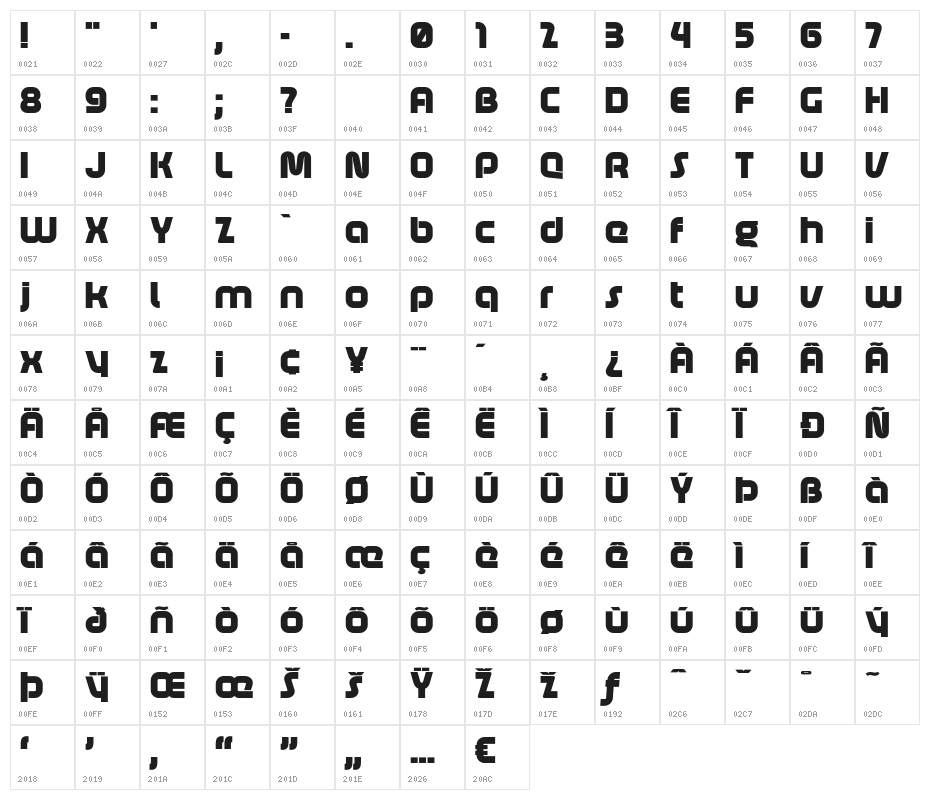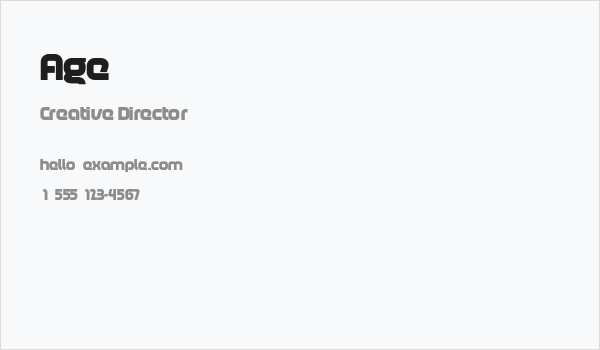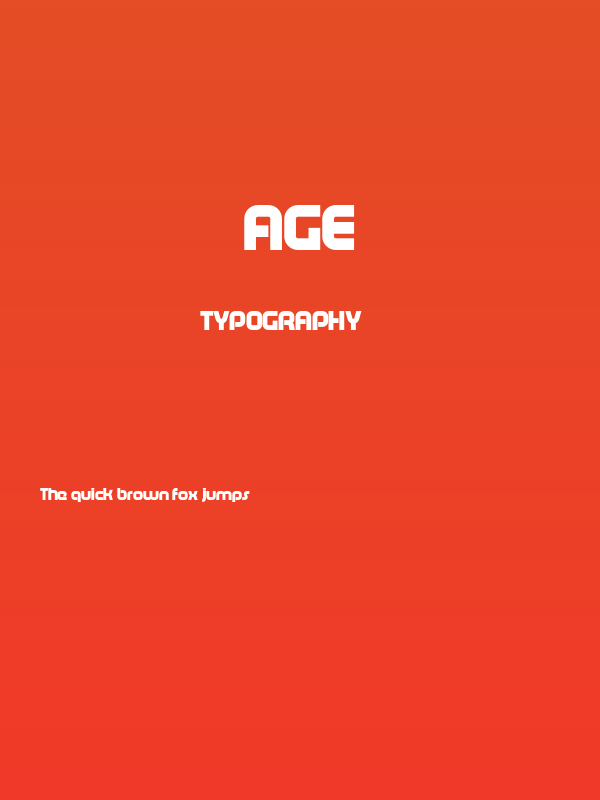
Age Font
✎ Round
| カテゴリ | Round |
| おすすめプロジェクト | Ideal for branding, headlines, posters, and digital media where a strong, modern presence is desired. |